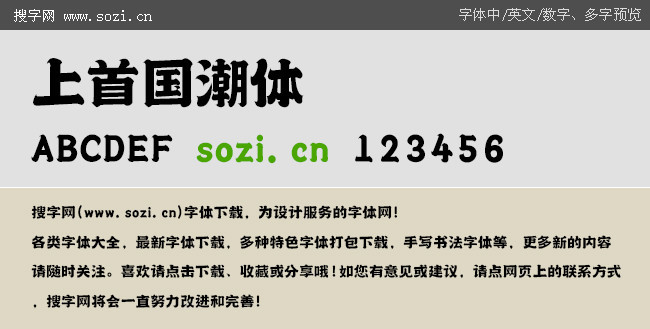
上首國潮體
搜字網(wǎng)給大家提供一款上首國潮體中文字體下載,上首國潮體字體是字體傳統(tǒng)漢字文化與現(xiàn)代藝術相結合打造的—款字體,字體中的橫豎筆畫粗細一致,字型勻稱,結構端正,橫平豎直,嚴謹規(guī)整,完美的給大家呈現(xiàn)出了一種嚴謹、精簡的感覺,適用于搭配標志、廣告標語、商業(yè)廣告等廣告設計。